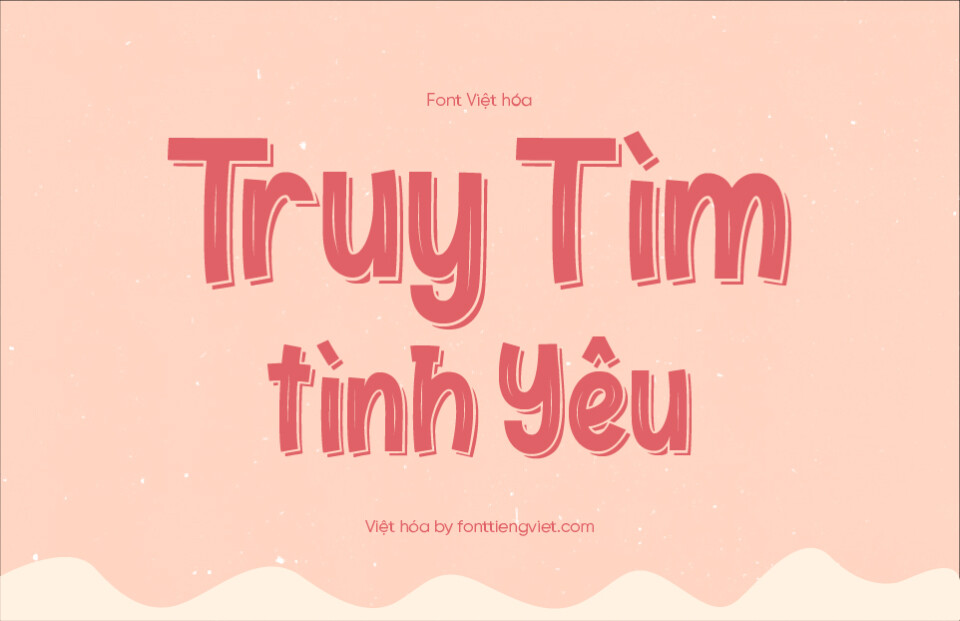
Font Việt hóa 1FTV VIP Bubble Love – Font cho Valentine
Font Việt hóa 1FTV VIP Bubble Love – Font cho Valentine siêu lãng mạn
Ngày Lễ Tình nhân đang đến gần, nhu cầu tìm kiếm những bộ Font Miễn Phí để thiết kế thiệp mừng và quà tặng ngày càng tăng cao. Trong số đó, Font Việt hóa 1FTV VIP Bubble Love – Font cho Valentine nổi lên như một lựa chọn hoàn hảo nhờ phong cách ngọt ngào, mềm mại và tràn đầy cảm hứng yêu thương. Đây là bộ font chữ không thể thiếu đối với các bạn học sinh, sinh viên và những nhà sáng tạo nội dung muốn gửi gắm thông điệp chân thành qua từng nét chữ.
Khám phá sức hút của Font Việt hóa 1FTV VIP Bubble Love – Font cho Valentine
Thiết kế bong bóng độc đáo và bắt mắt
Đúng như tên gọi, Font Việt hóa 1FTV VIP Bubble Love – Font cho Valentine mang phong cách “bubble” với các đường nét tròn trịa, tạo cảm giác như những bong bóng xà phòng bay bổng. Các ký tự được uốn lượn tỉ mỉ, giúp tổng thể bản thiết kế trở nên sống động và thân thiện hơn bao giờ hết. Sự kết hợp giữa nét dày và các khoảng bo tròn khiến bộ font này cực kỳ nổi bật trên các nền màu pastel hoặc đỏ hồng đặc trưng của ngày Valentine.
Khả năng ứng dụng linh hoạt trong giáo dục và thiết kế
Không chỉ dùng cho các cặp đôi, bộ font này còn được ưa chuộng trong môi trường học đường để trang trí bảng tin, thiết kế slide thuyết trình hay làm báo tường. Nhờ đã được Việt hóa hoàn chỉnh, người dùng có thể thoải mái gõ tiếng Việt có dấu mà không lo bị lỗi hiển thị. Điều này giúp các bạn học sinh dễ dàng thể hiện sự sáng tạo trong các dự án nghệ thuật cá nhân.
Hướng dẫn sử dụng font hiệu quả
Để tận dụng tối đa vẻ đẹp của bộ font này, bạn nên kết hợp với các tông màu ấm áp. Việc thêm các hiệu ứng đổ bóng hoặc viền trắng sẽ giúp chữ viết trông như những viên kẹo ngọt ngào, tăng thêm tính thẩm mỹ cho tác phẩm. Hãy tải ngay Font Miễn Phí, Font Việt Hóa, Font Việt hóa 1FTV VIP Bubble Love – Font cho Valentine để bắt đầu hành trình sáng tạo của mình ngay hôm nay.